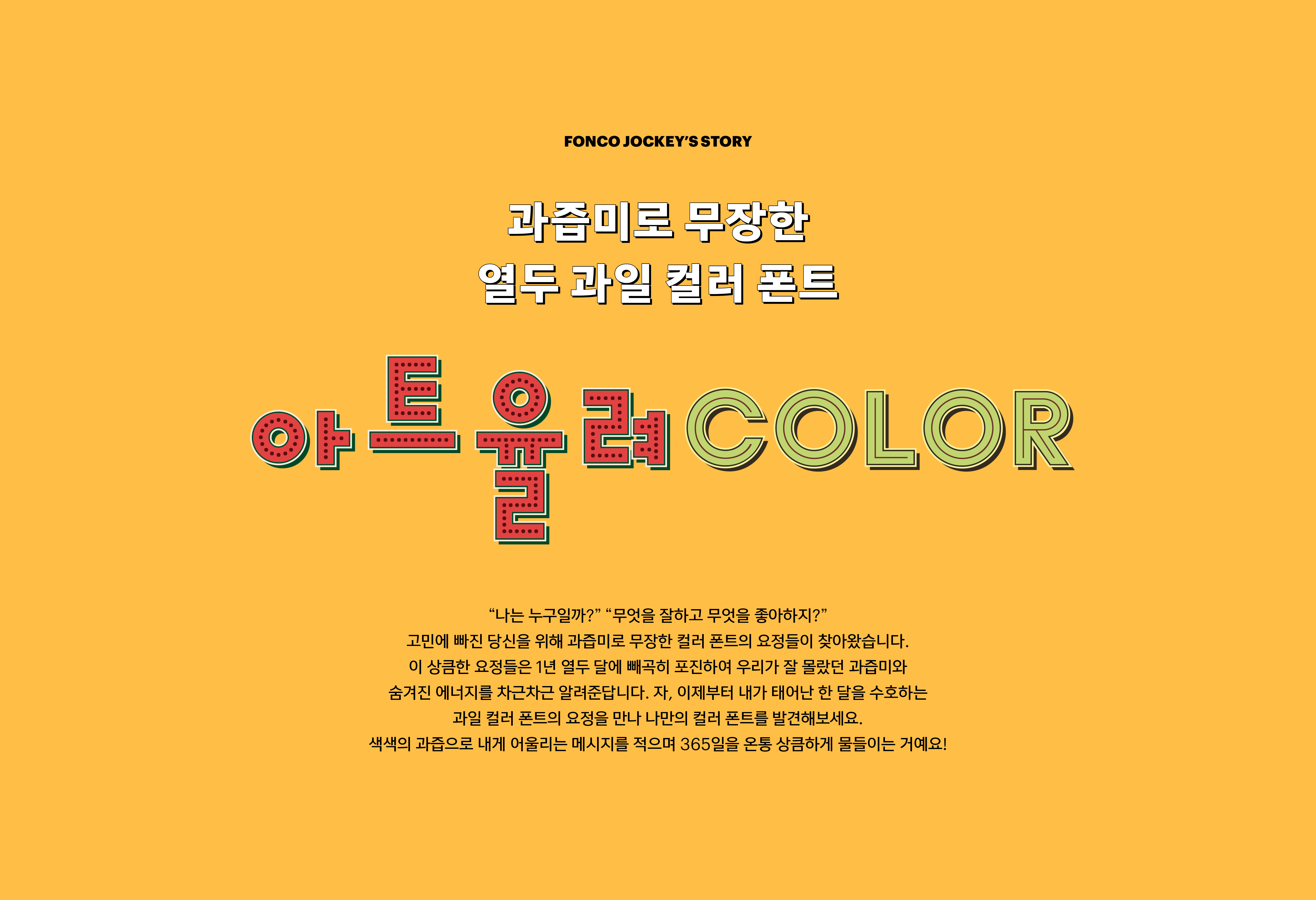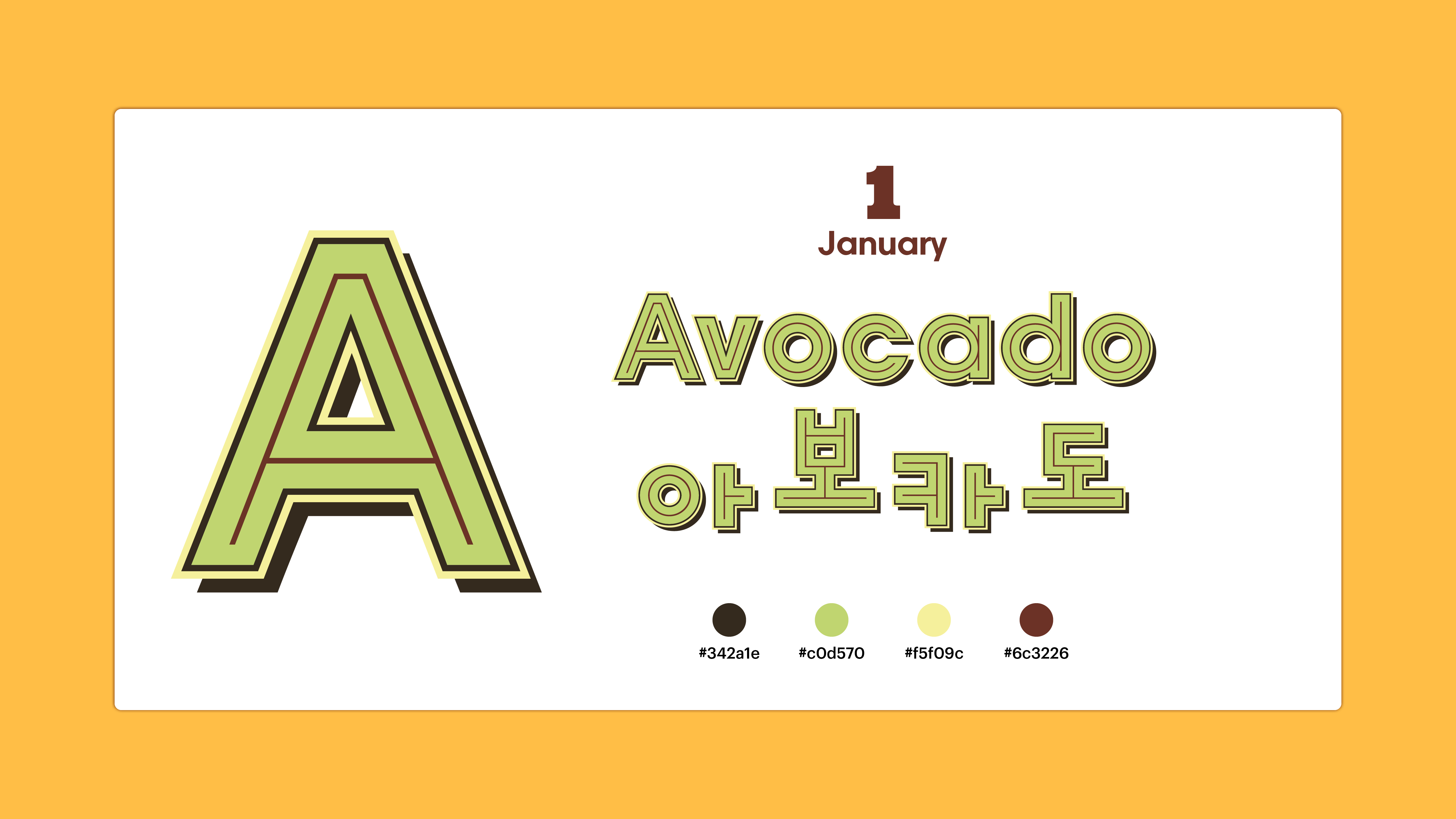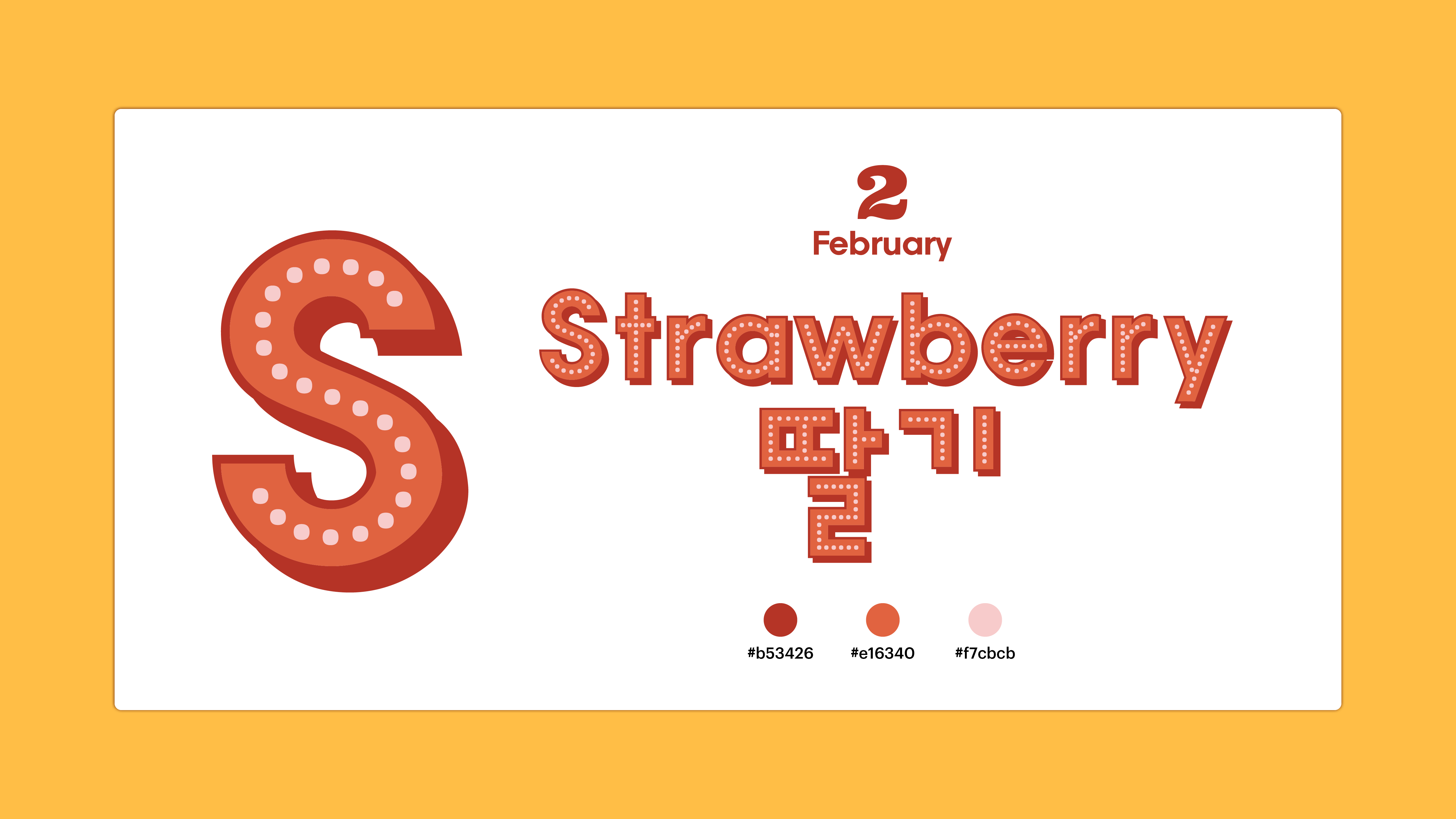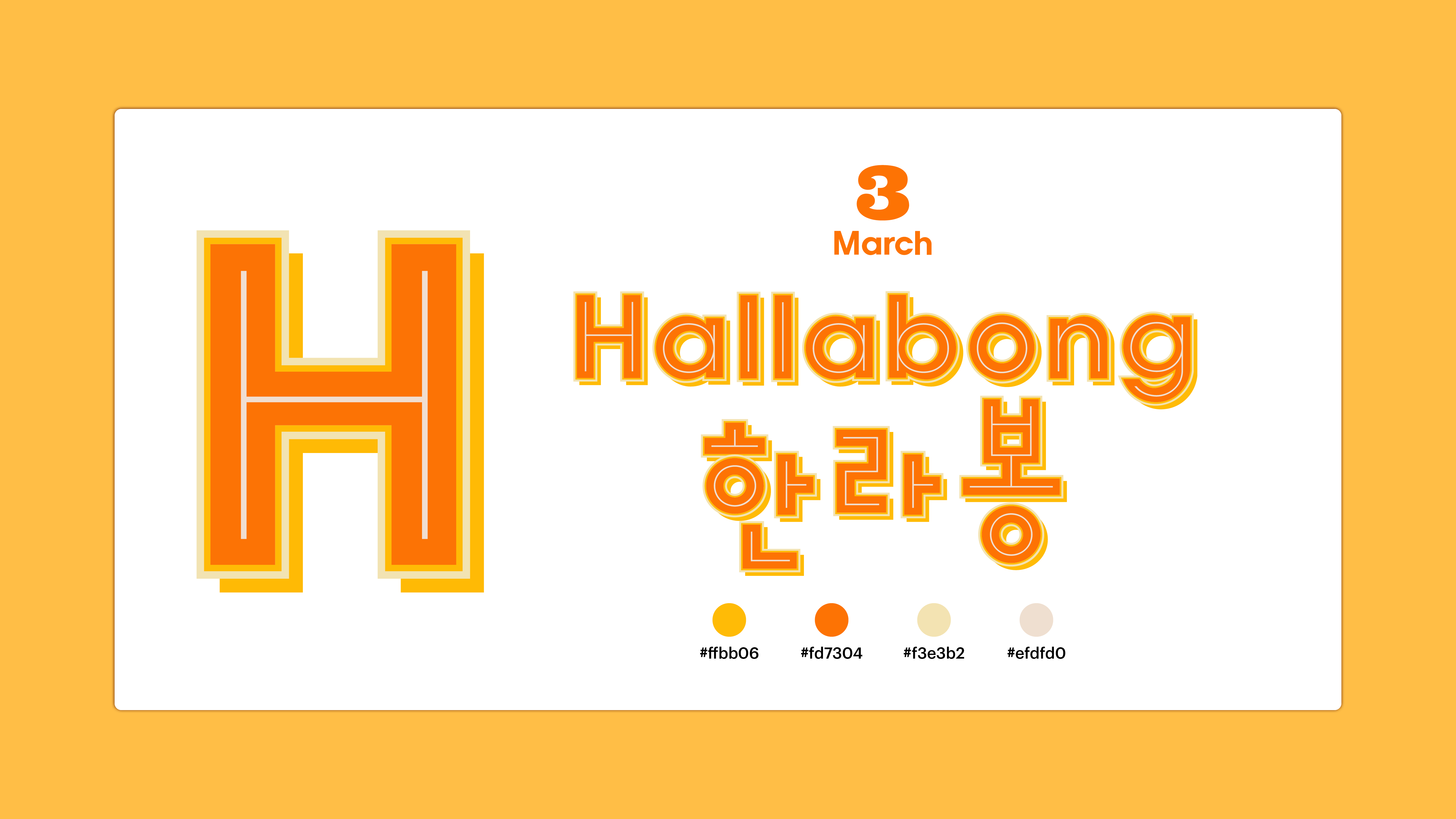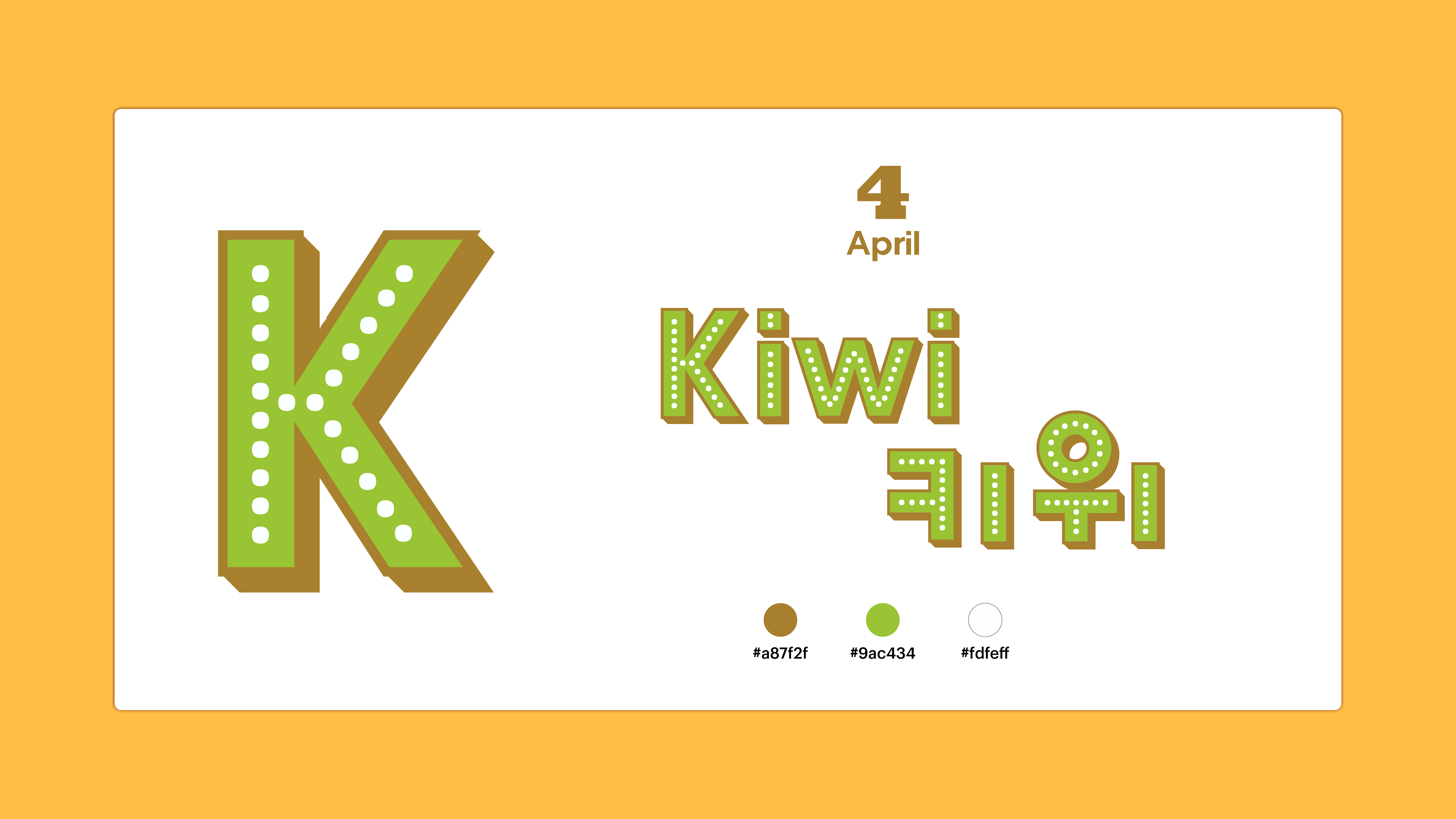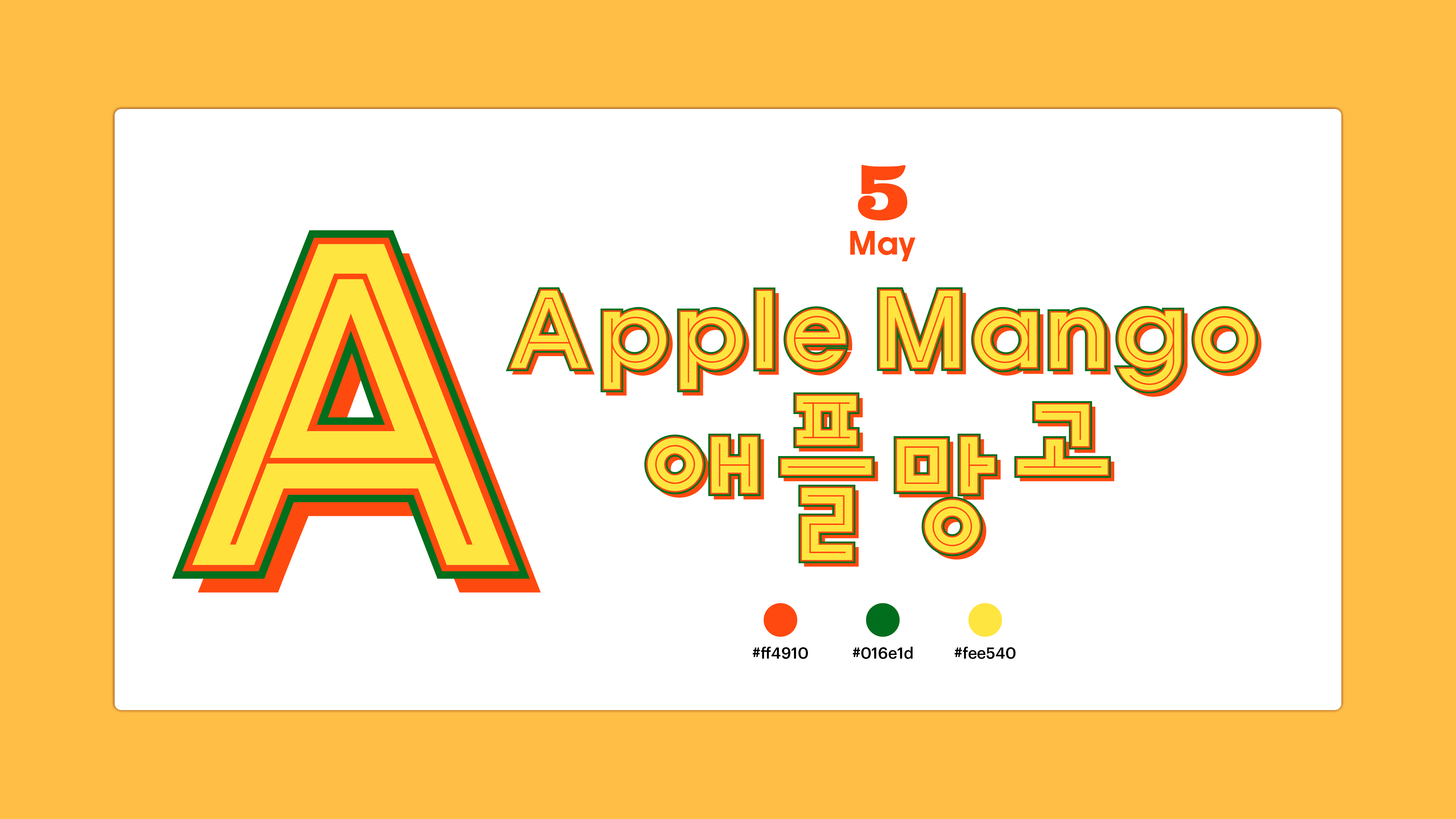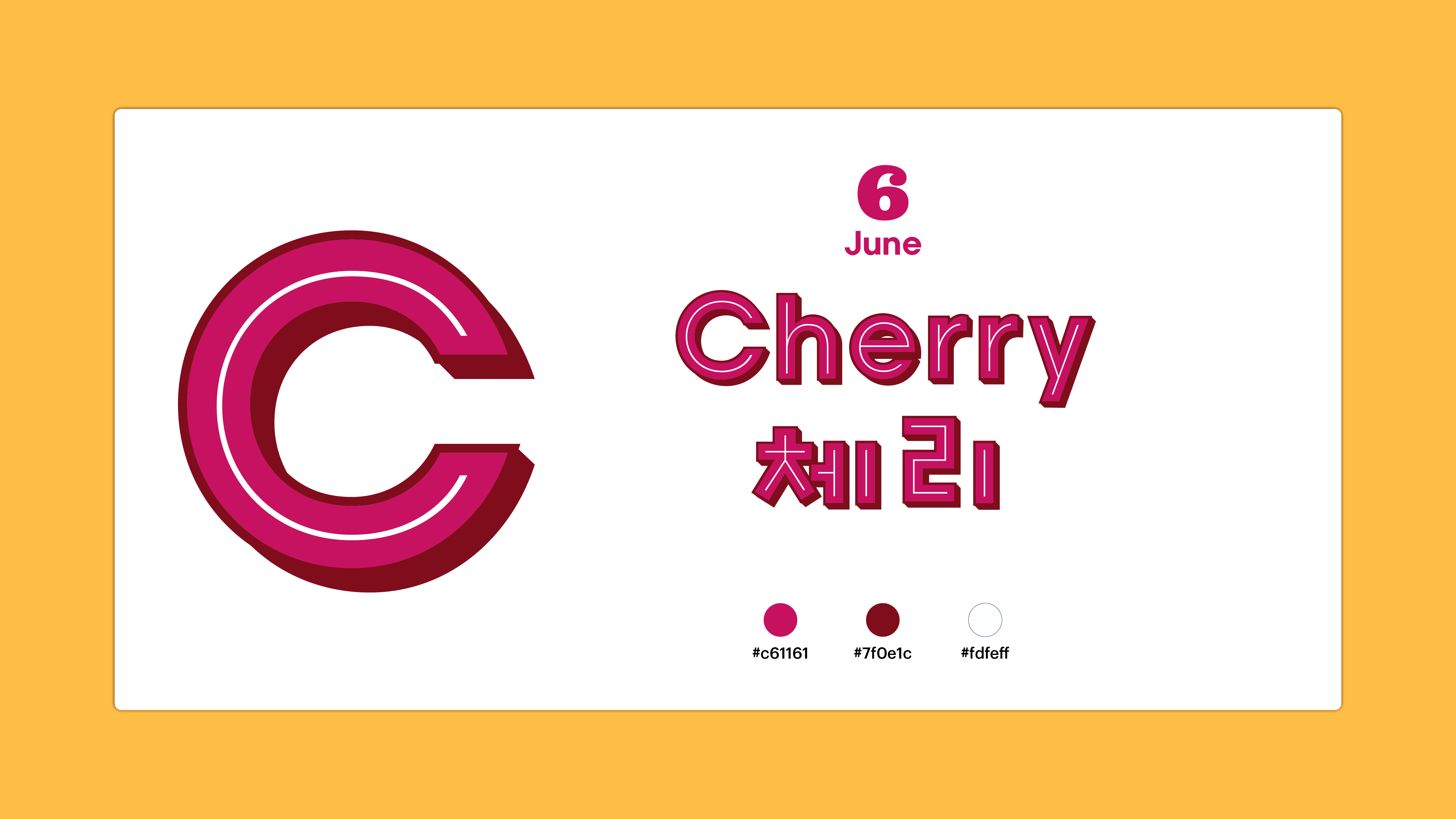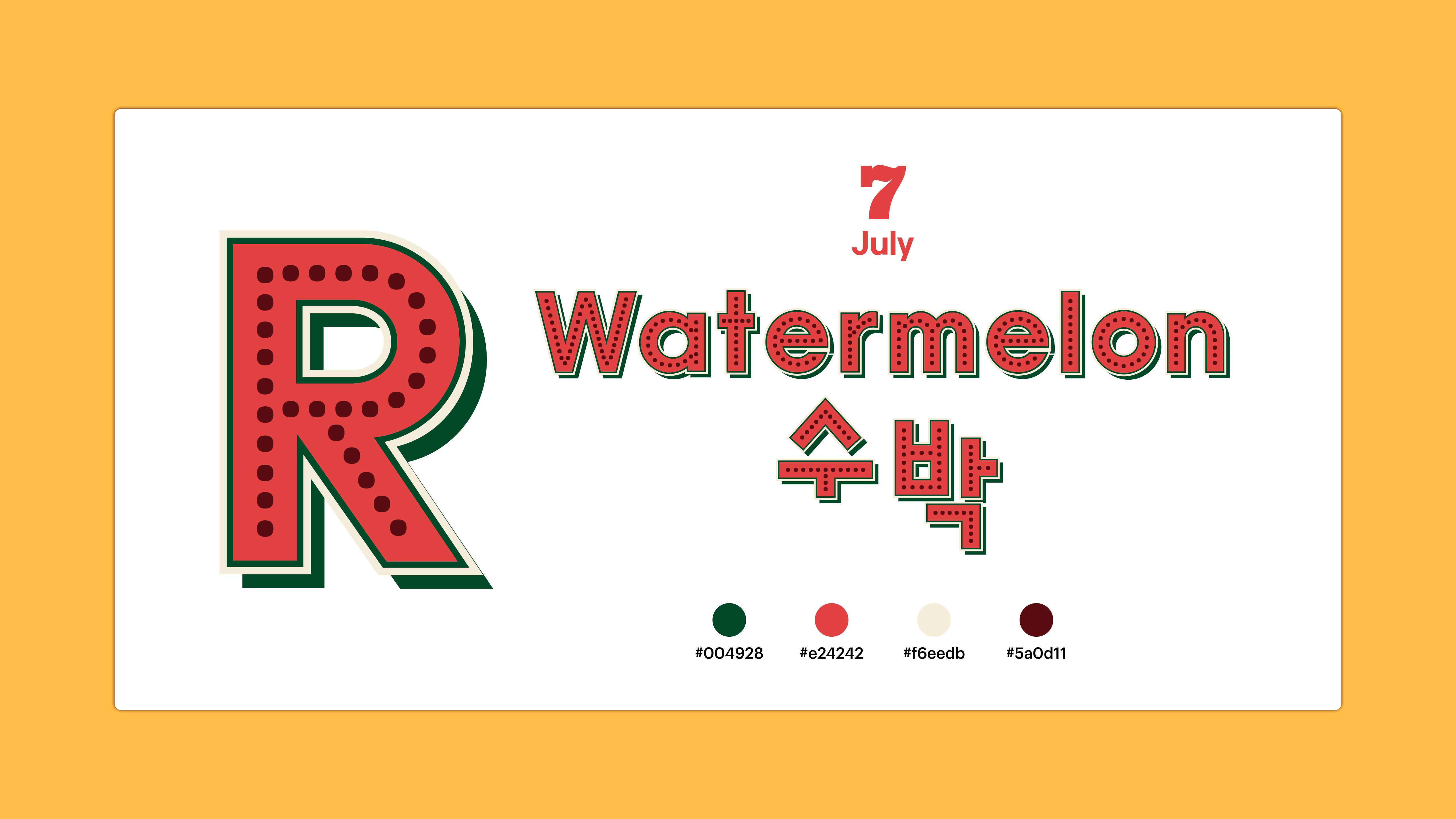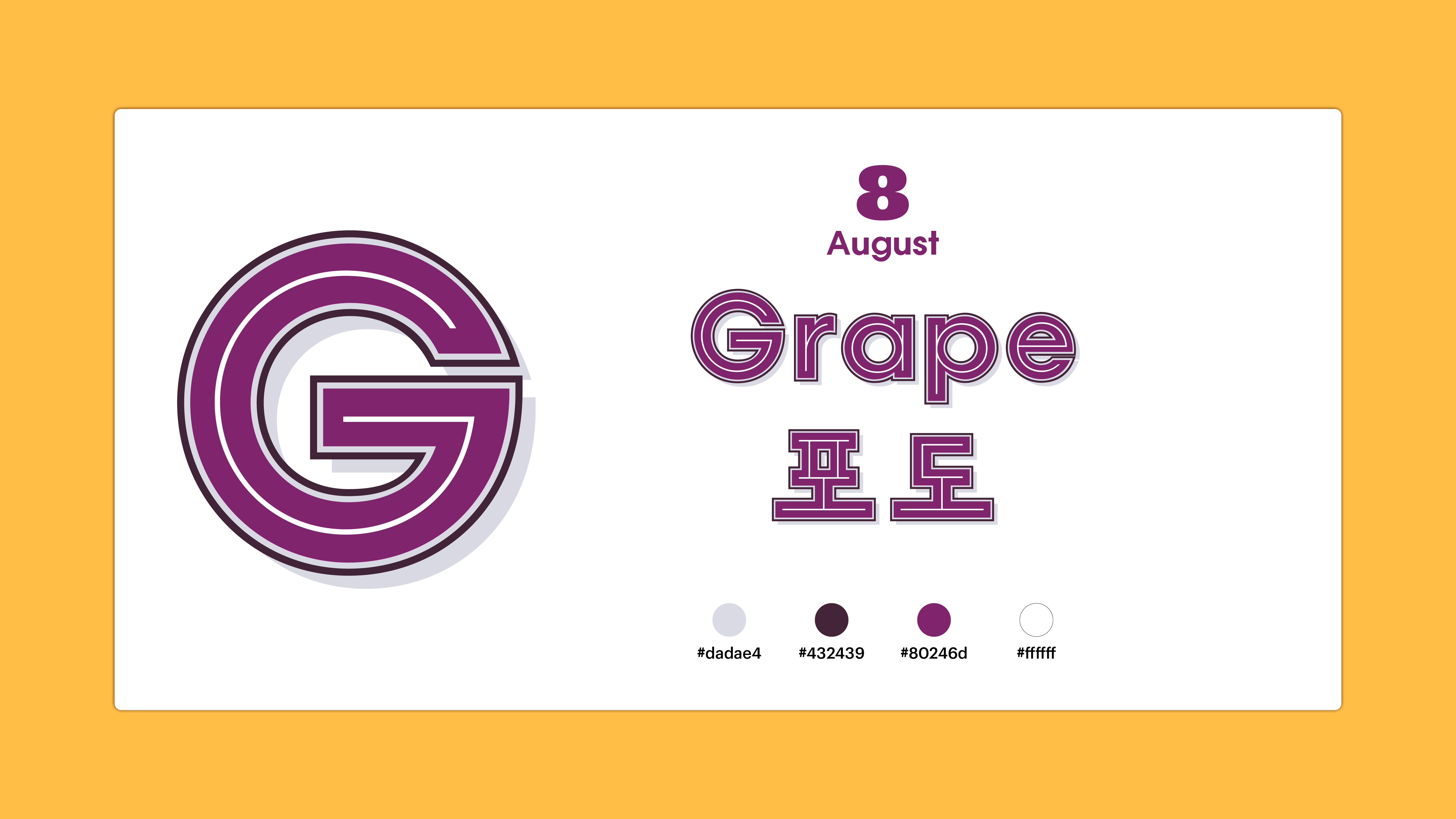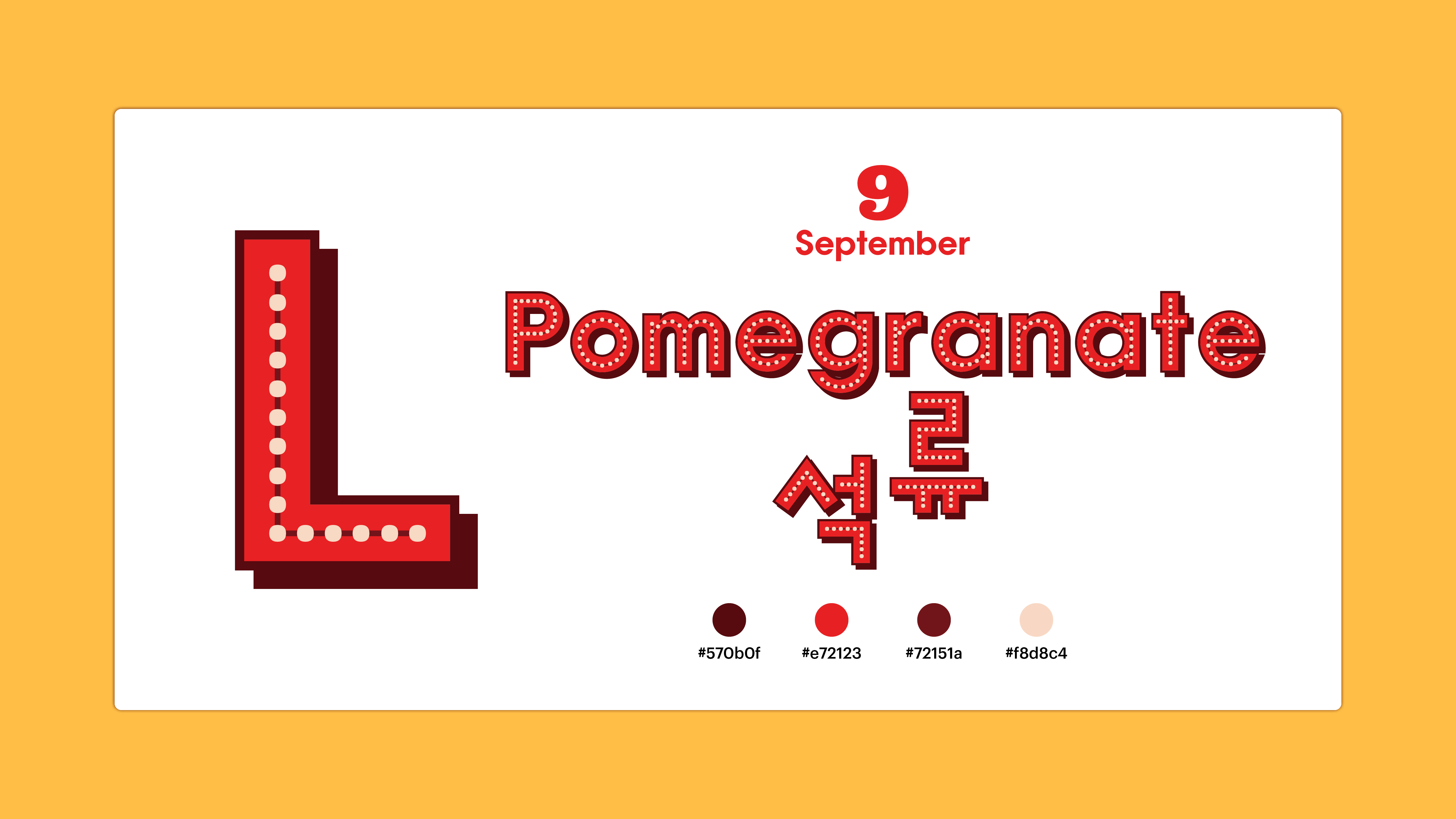
"나는 누구일까?" "무엇을 잘하고 무엇을 좋아하지?" 고민에 빠진 당신을 위해 과즙미로 무장한 컬러 폰트의 요정들이 찾아왔습니다. 이 상큼한 요정들은 1년 열두 달에 빼곡히 포진하여 우리가 잘 몰랐던 과즙미와 숨겨진 에너지를 차근차근 알려준답니다. 자, 이제부터 내가 태어난 한 달을 수호하는 과일 컬러 폰트의 요정들을 만나 나만의 컬러 폰트를 발견해보세요. 색색의 과즙으로 내게 어울리는 메시지를 적으며 365일을 온통 상큼하게 물들이는 거예요!
Yoon 아트율려 Color